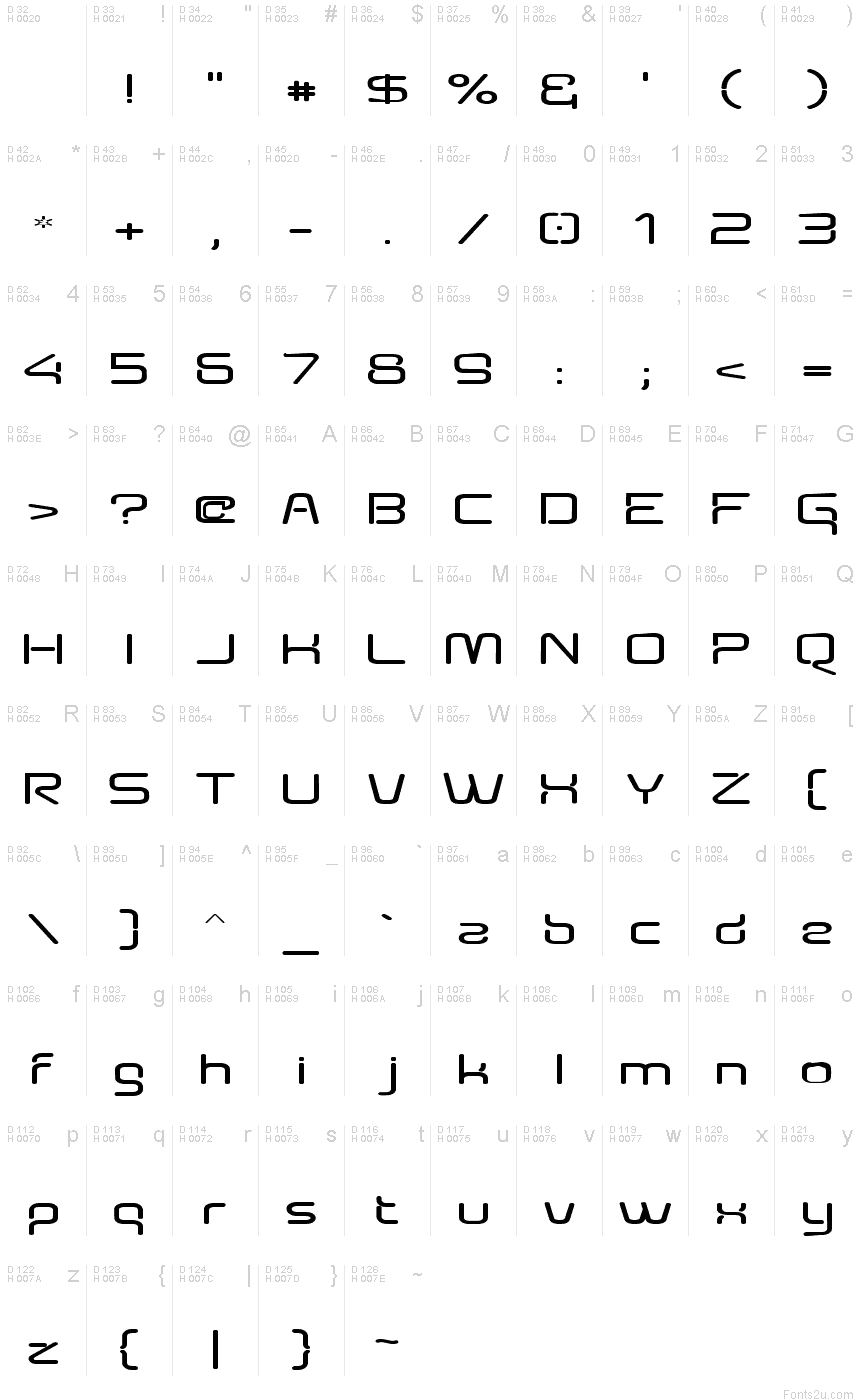
Aunchanted Expanded Bold
Aunchanted Expanded Bold von Graham Meade ist eine kostenlose, futuristische Display-Schrift mit einem eleganten, weichen Sci-Fi-Touch. Die Buchstaben kombinieren breite, abgerundete Formen mit eingeschnittenen Öffnungen und ungewöhnlichen Verbindungen. Das verleiht der Schrift einen stromlinienförmigen, fast synthetischen Rhythmus, der eher an eine UI-Oberfläche als an eine klassische geometrische Sans Serif erinnert.
Sie passt perfekt zu Postern, Game-Branding, Musik-Artworks, Tech-Event-Grafiken und Titelkarten, bei denen kurze Zeilen eine klare, zukunftsweisende Stimme brauchen. Als kostenlose Schrift eignet sie sich auch hervorragend für Logos, Cover-Lines und Monogramme, da die abgerundeten Formen und die präzisen Details selbst wenigen Buchstaben einen durchdachten und unverwechselbaren Charakter verleihen.